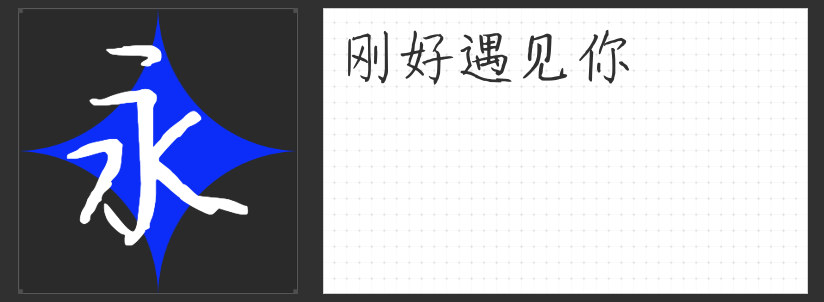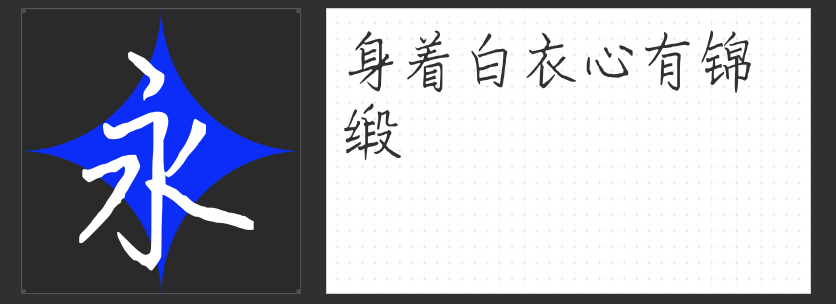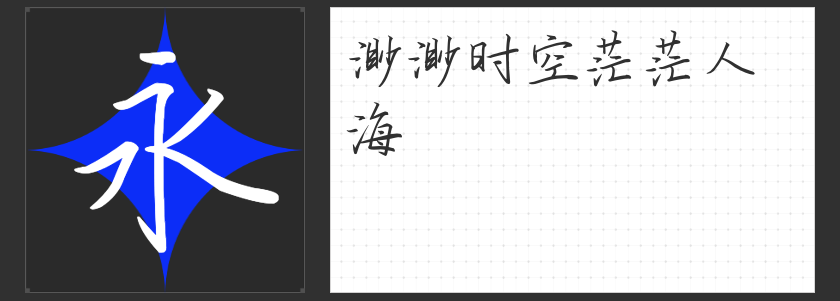
墨韵长存:四款怀旧手写字体唤醒时光记忆
在数字化浪潮中,手写字体以其独特的温度感成为设计领域不可或缺的怀旧符号。本次精选四款饱含传统书卷气的手写字体,带您回溯笔墨丹青的时代记忆。
一、云书法惠中行书体
这款字体如文人信札般温润,行笔介于楷草之间,既保留楷书端方骨架,又融入草书连笔意趣。牵丝萦绕处似见笔锋转折,工整中透出灵动,特别适合复古书信模板、古籍再版设计。其舒展的笔画自带故事感,仿佛能听见笔尖与宣纸摩擦的沙沙声。
二、云书法罗西硬笔楷书体
这款楷书如文人立于书案前,提按顿挫间尽显风骨。中锋运笔的遒劲与墨色浓淡的层次,在硬核笔触中保留毛笔飞白韵味。章法布局疏朗有致,适合传统品牌LOGO、古籍研究著作等场景,数字时代仍能传递竹简木牍的沉香。
三、 云书法硬笔颜楷简
取法颜真卿的雄浑气度,这款字体将碑刻拓片质感凝于笔尖。横竖如刀刻斧凿,捺画似惊鸿掠影,方正架构中暗藏动态平衡。适用于历史题材纪录片字幕、文化展览导视系统,让观者触摸到千年碑林的岁月包浆。
四、 励字行草简繁
这款行草如侠客醉后挥毫,既有行书的章法可循,又具草书的率性洒脱。连笔处如疾风扫落叶,留白间似云海生明月,适合武侠游戏界面、摇滚专辑封面等需要强烈表现力的场景。简繁双版本更可营造时空交叠的蒙太奇效果。
四款字体如同打开四卷泛黄的手抄本,既有文人士大夫的笔墨清趣,亦含江湖艺人的挥洒豪情。在国潮复兴的今天,这些跨越时空的书写痕迹,恰似数字洪流中的磐石,让设计作品在效率之外,更添一份可触摸的文化厚度。